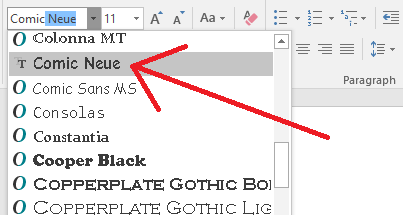
Apa Itu Font Family – Font family adalah konsep dalam desain tipografi yang merujuk pada kumpulan gaya atau variasi huruf yang memiliki karakteristik serupa, tetapi memiliki berbagai bobot, ketebalan, dan gaya. Dalam dunia desain grafis dan pengolahan teks, pemilihan font family memainkan peran krusial dalam membentuk tampilan visual dan merancang pesan yang ingin disampaikan.
Font family terdiri dari tiga komponen utama: jenis huruf (serif, sans-serif, monospace, dll.), bobot (light, reguler, bold, dll.), dan gaya (italic, oblique). Misalnya, dalam font family “Arial”, “Arial” adalah jenis hurufnya, sementara “Regular” atau “Bold” adalah bobotnya, dan “Italic” atau “Oblique” adalah gayanya. Font family yang umum digunakan termasuk Times New Roman, Arial, Helvetica, dan banyak lagi.
Tips Pemilihan Font Family yang Cocok
Pemilihan font family mempengaruhi citra dan pesan yang ingin disampaikan dalam dokumen atau desain, setelah kita membahas tentang apa itu font family dan beberapa penjelasannya kali ini kita akan memberikan beberapa tips memilih font yang tepat. Font serif, dengan dekorasi tambahan pada ujung karakter, sering digunakan untuk menciptakan kesan formal dan tradisional. Sebaliknya, font sans-serif yang lebih bersih dan tanpa ornamen cenderung memberikan kesan modern dan bersih. Selain itu, variasi bobot dan gaya dalam font family dapat digunakan untuk menyoroti bagian teks tertentu, memberikan hierarki visual, atau menambahkan dimensi artistik pada desain.
Dalam proses desain grafis, pemilihan font family yang tepat juga mempertimbangkan konsistensi dan keberlanjutan. Menggunakan beberapa font family yang tidak sejalan dapat menciptakan tampilan yang tidak teratur dan membingungkan bagi pembaca. Sebaliknya, konsistensi dalam font family membantu menciptakan identitas visual yang kuat dan mudah diingat.
Dengan kemajuan teknologi, desainer sekarang memiliki akses ke berbagai font family melalui perpustakaan online dan alat desain. Ini memungkinkan kreasi visual yang lebih kreatif dan beragam, memungkinkan desainer untuk menyesuaikan presentasi teks dengan karakter dan kebutuhan spesifik proyek.
Dalam menggali dunia desain, pemahaman tentang font family bukan hanya tentang estetika visual tetapi juga tentang komunikasi yang efektif dan ekspresi desain yang tepat. Pemilihan yang cermat akan membantu menciptakan desain yang menarik dan dapat dipahami, memperkuat pesan yang ingin disampaikan melalui media visual.